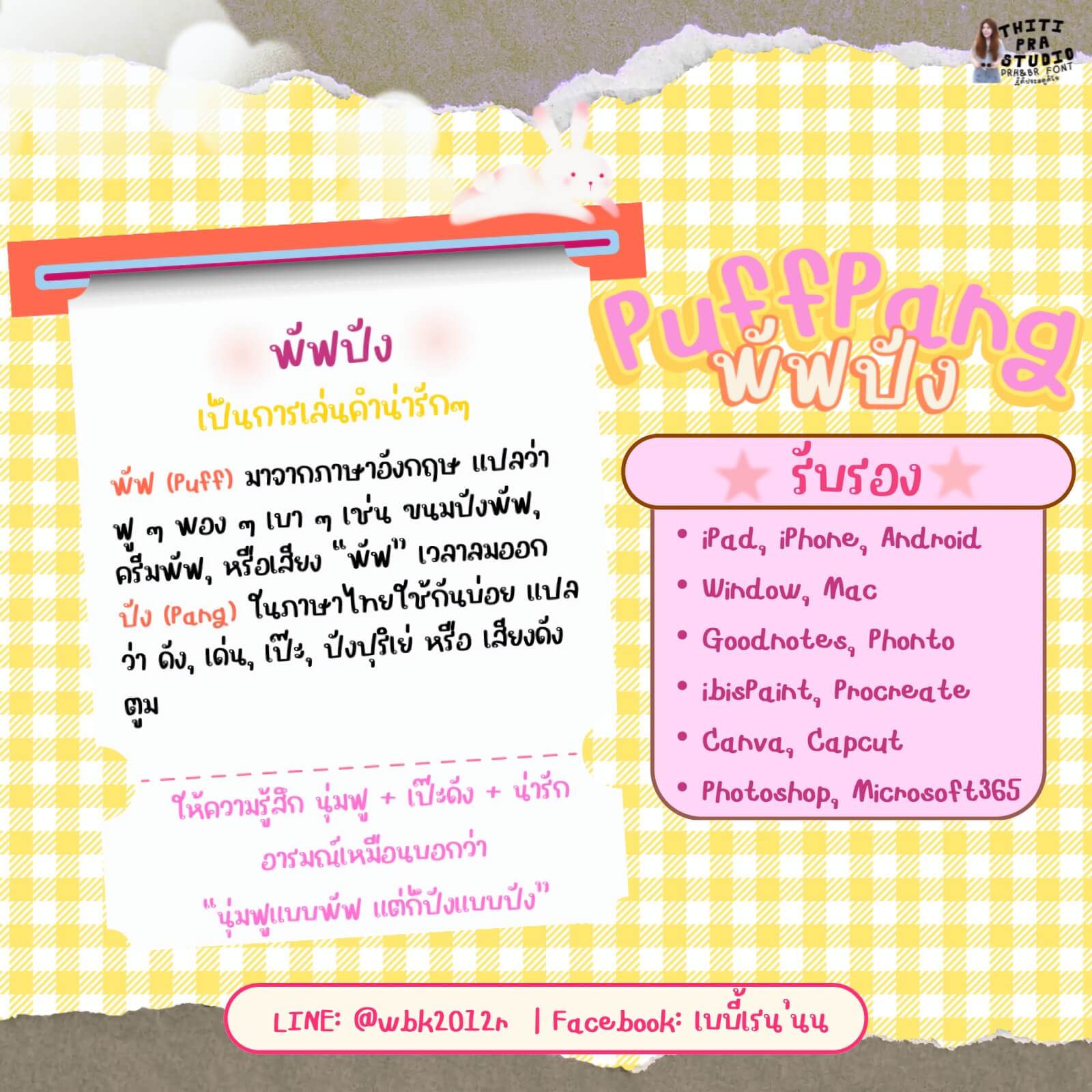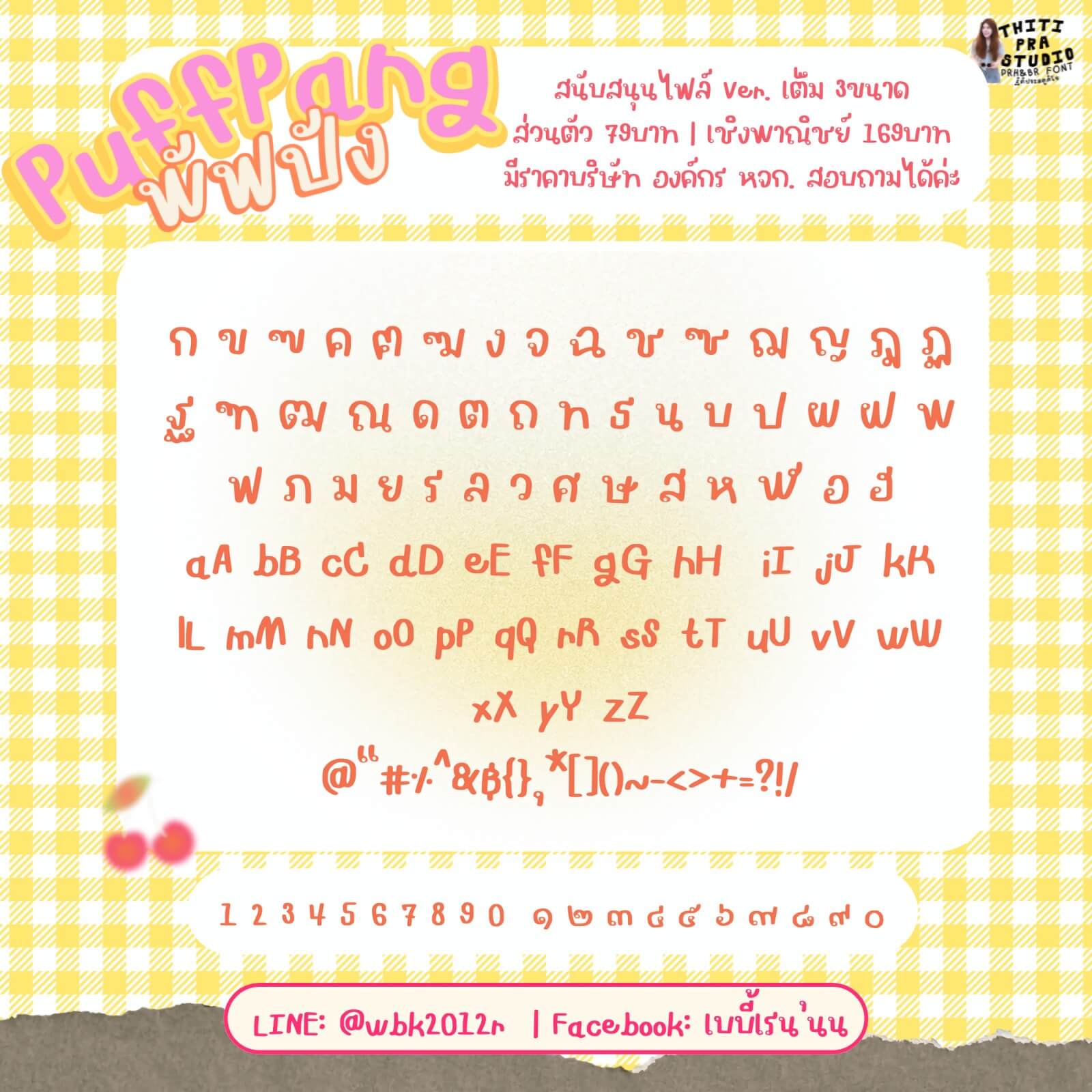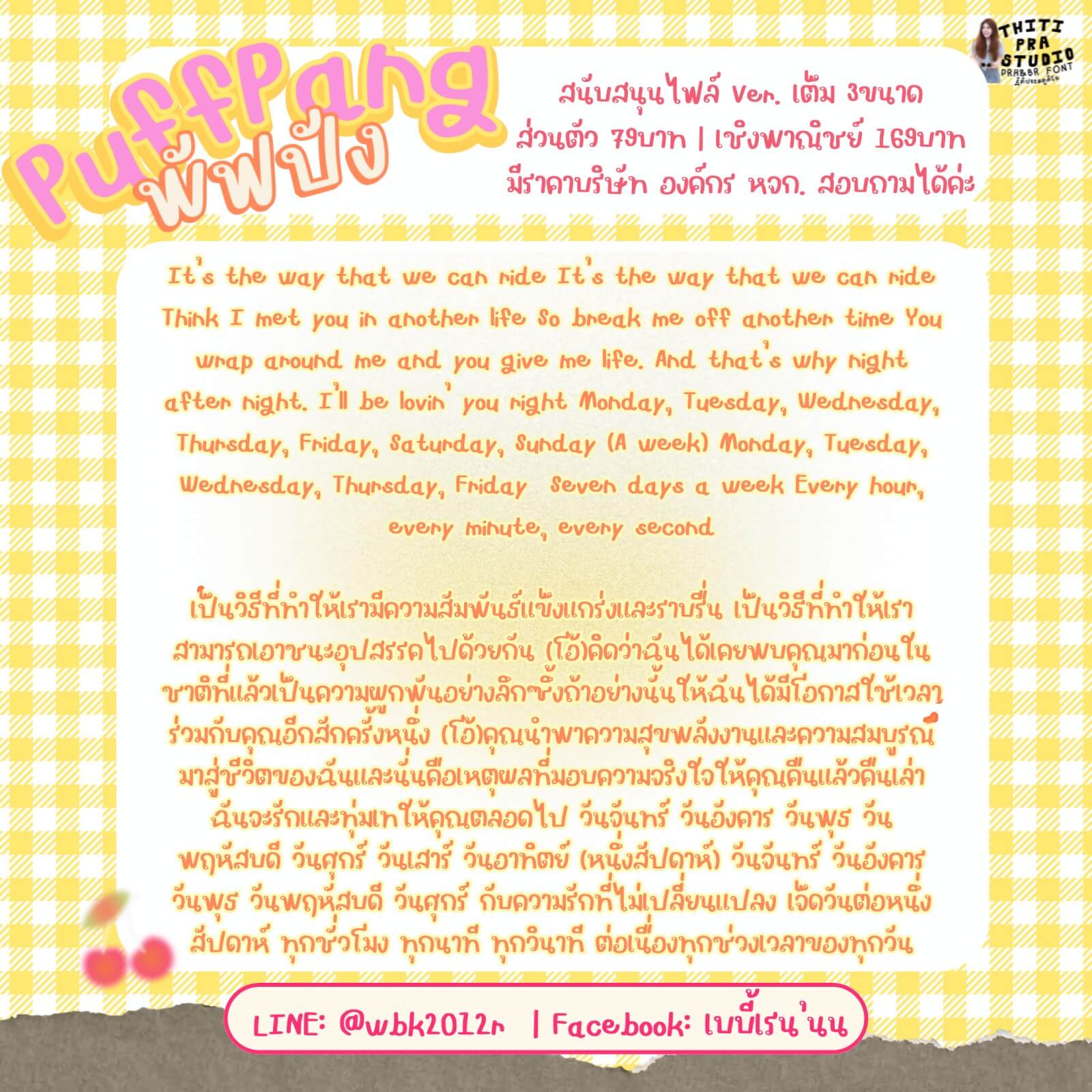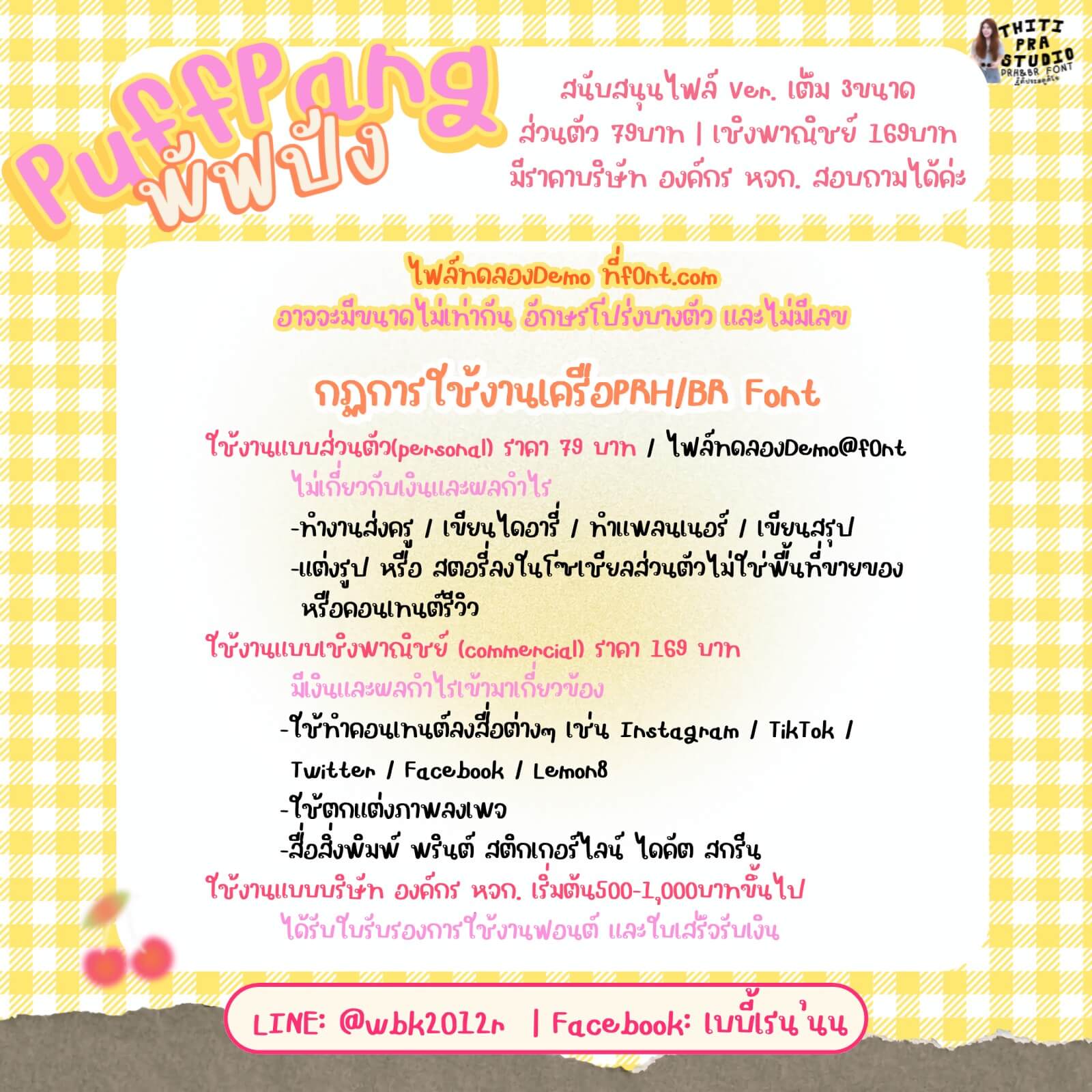
พัฟปัง (PRHPuffPang)
PRHPuffPang  / พัฟปังฟอนต์ – ฟอนต์แนวโค้งมน น่ารักสดใส ให้ฟีลอ่อนโยนแนวเป็นกันเอง
• ฟอนต์มีขนาดไม่เท่ากัน / ไม่มีเลข/วรรณยุกต์ / อักษรโปร่งบางตัว